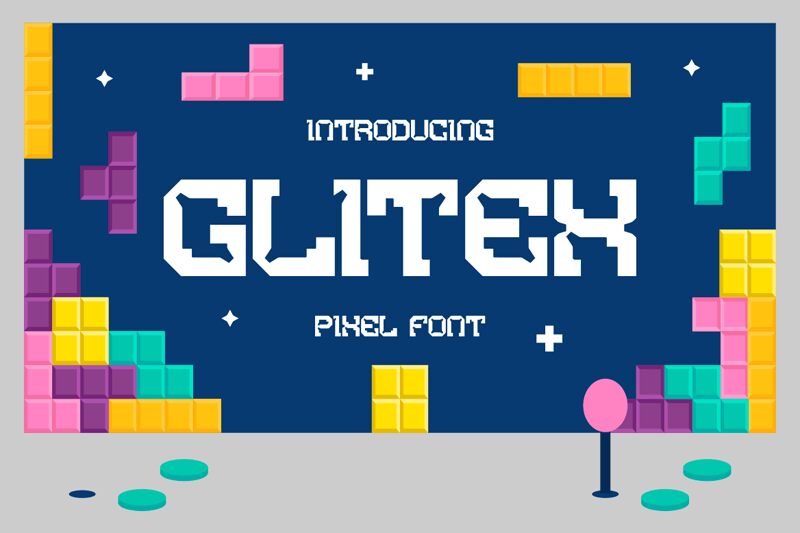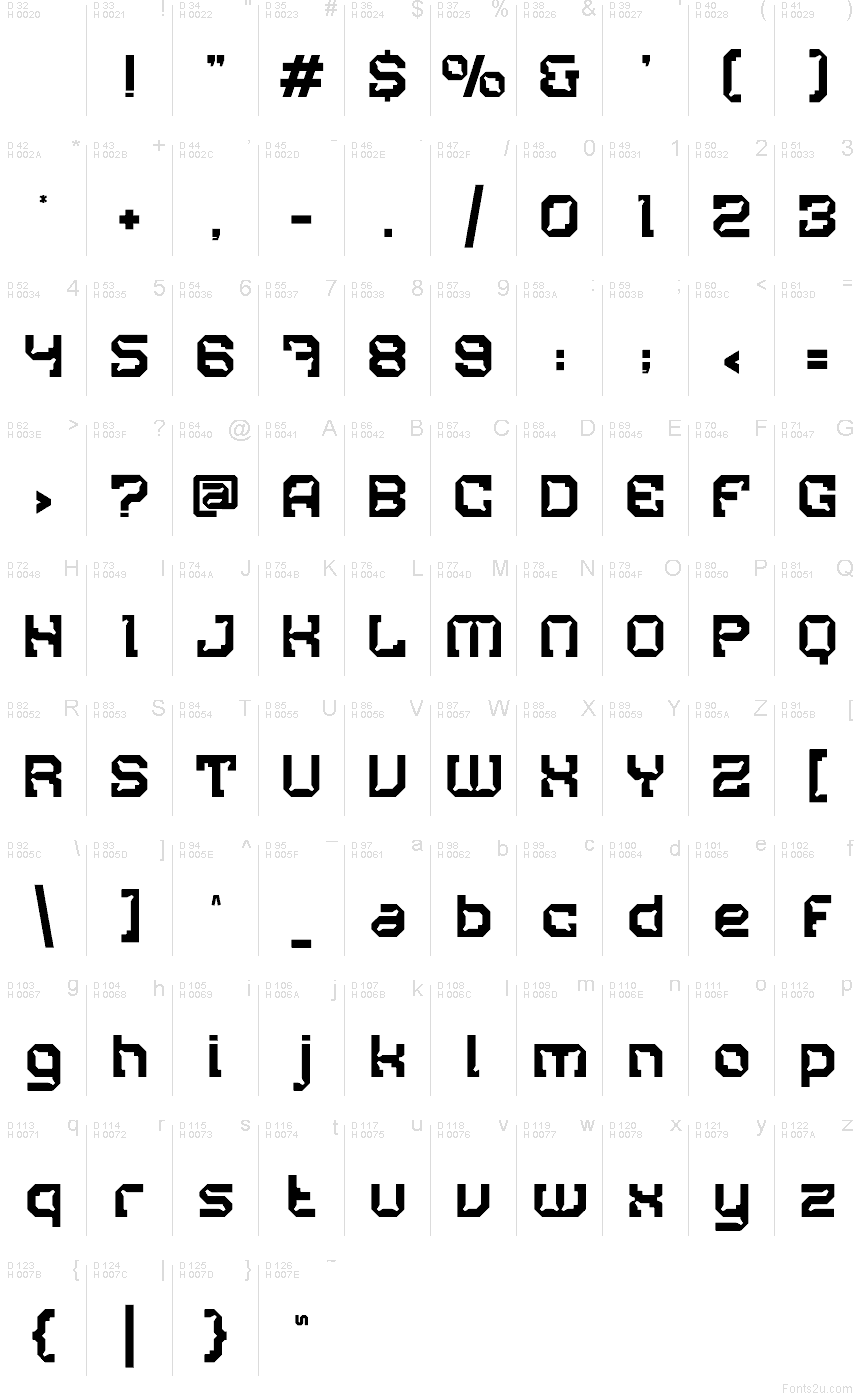
خط Glitex من Shanaf Studio هو خط عرض تكنو مجاني بحروف ضخمة مربعة ومظهر عريض يعكس بوضوح طابع ألعاب الآركيد. تكسر الشقوق العميقة والزوايا المشطوفة والفراغات الداخلية غير المنتظمة كثافة الخطوط، مما يمنح الحروف مظهر كتابة آلية مخصصة.
يمكنه تحويل عنوان لعبة أو شعار رياضة إلكترونية إلى عنصر مدمج من رسومات واجهة المستخدم، بتفاصيل حادة الزوايا تحاكي لوحات الـ HUD وأجهزة الخيال العلمي. وتناسب هذه الأشكال ذات الحواف الحادة أيضاً ملصقات الحفلات الموسيقية، وأزياء الشارع، والفعاليات المستقبلية.